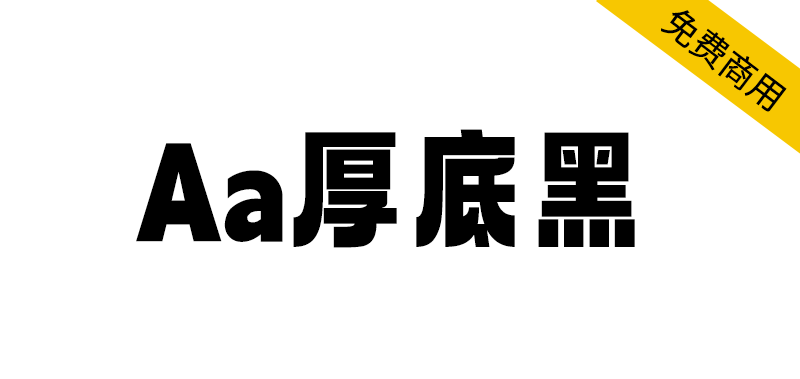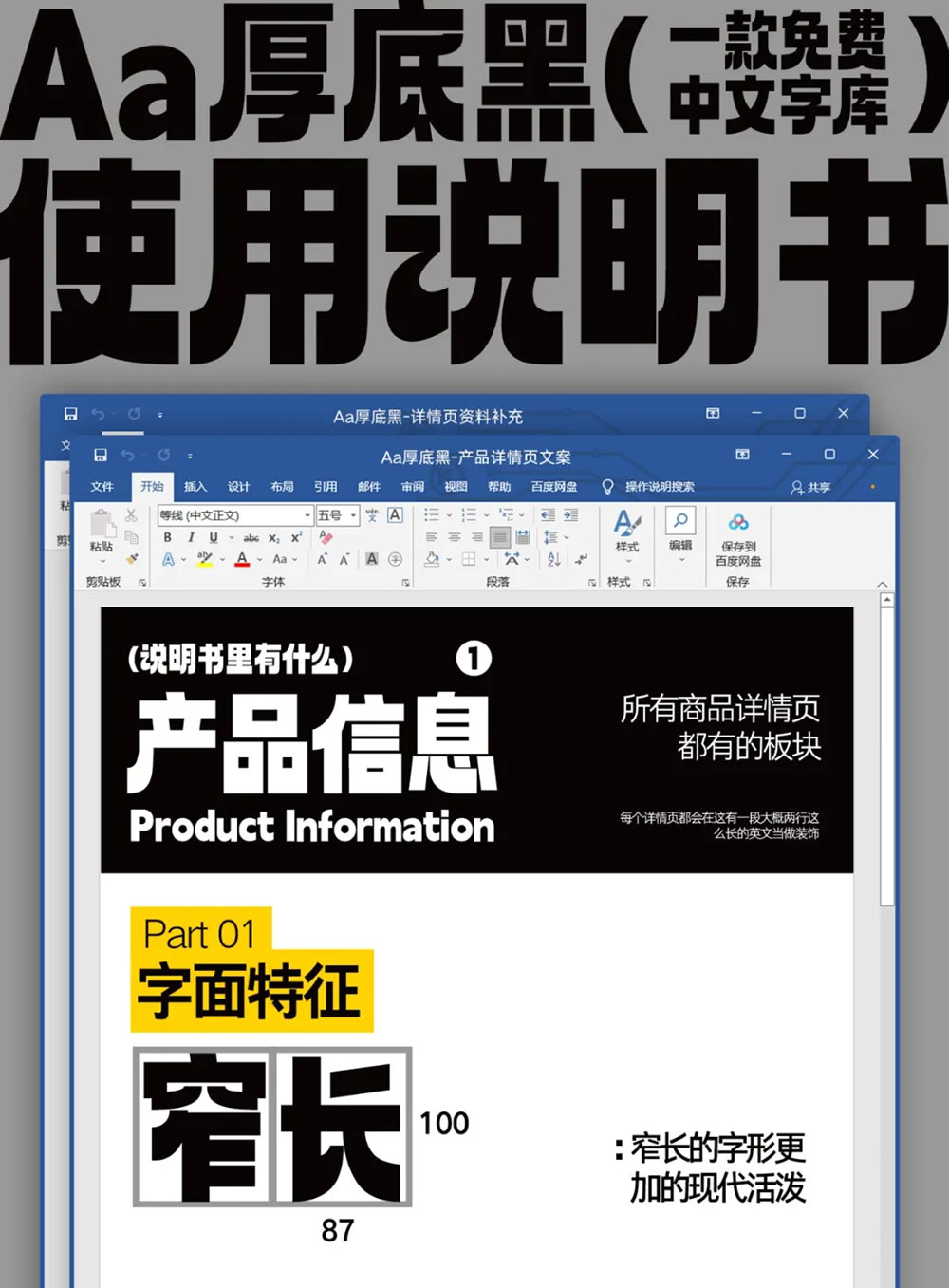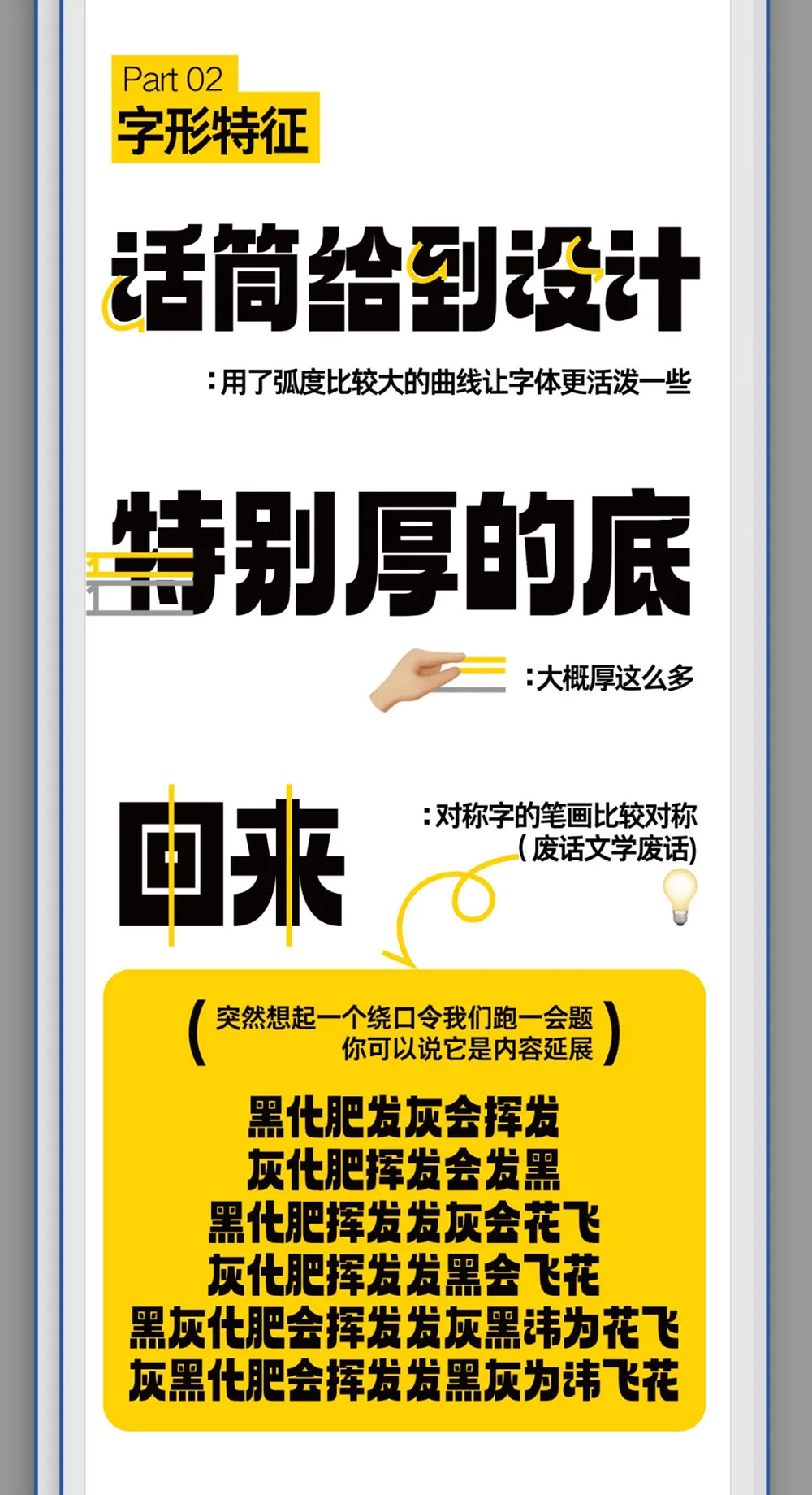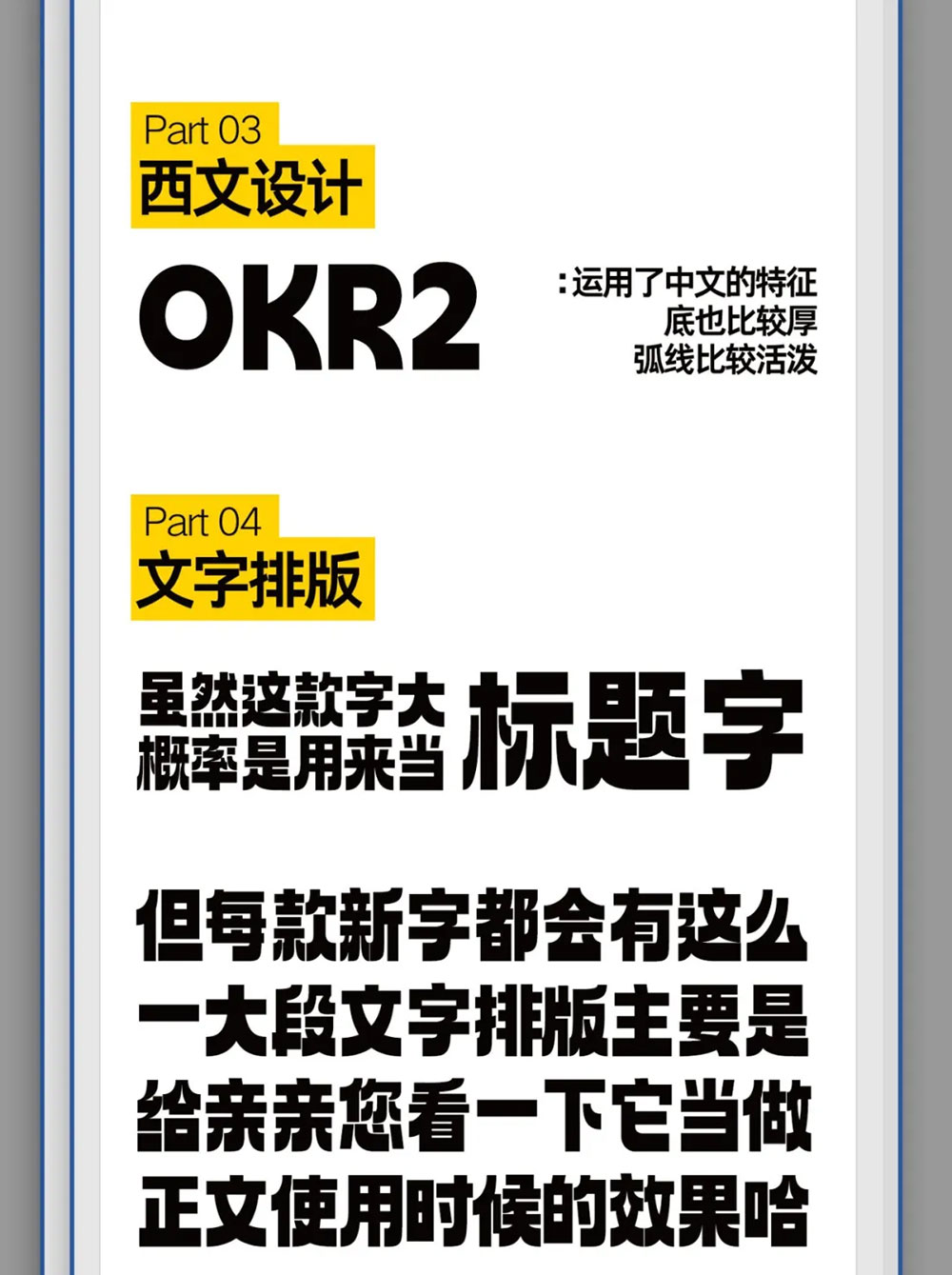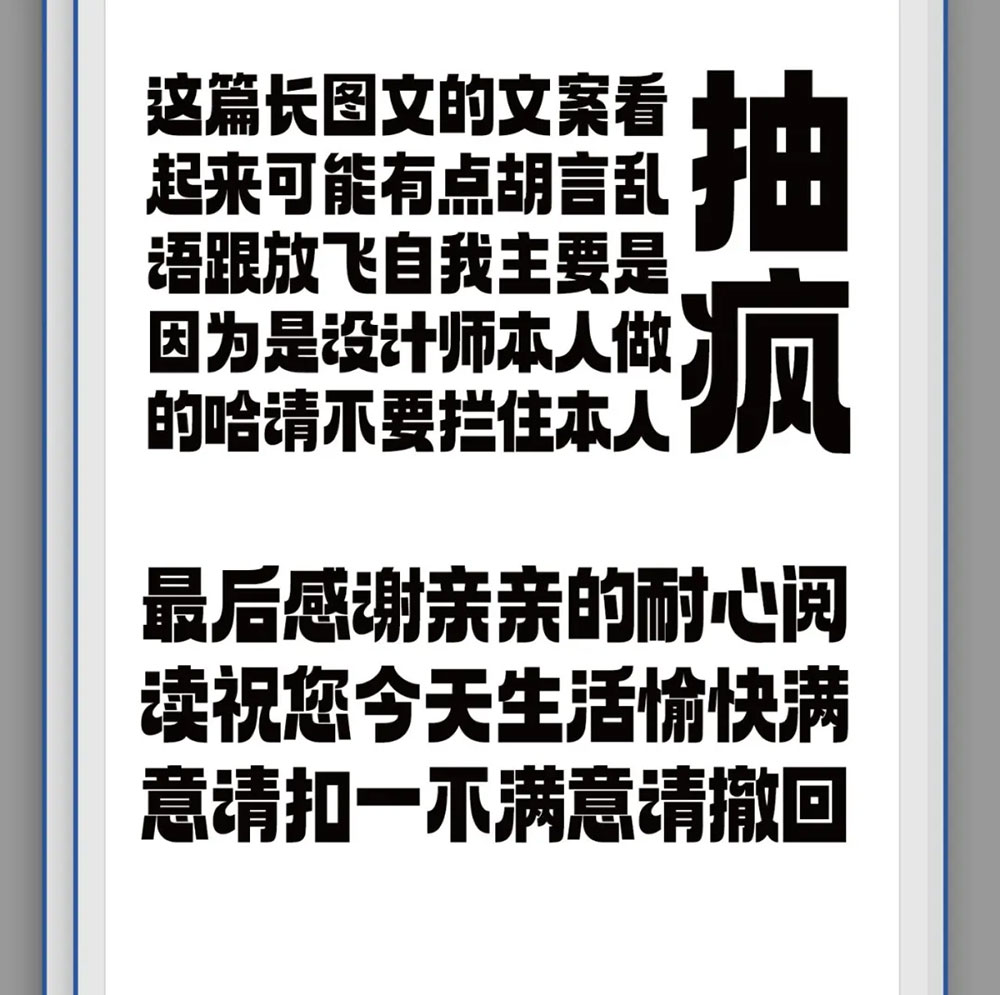
【Aa厚底黑】一款充满现代活泼的免费商用字体
Aa厚底黑是Aa字库推出的一款标题字体,其名称直观体现了字体的核心特征——厚重感与窄长造型的巧妙结合。这款字体在保持粗壮厚重风格的同时,通过修长的字形设计赋予了现代活泼感。
该字体的设计亮点在于:采用大弧度曲线处理,使厚重字形不失灵动;笔画经过精心加粗处理;西文字符完美延续中文字体的设计语言,同样具备厚底特征和流畅弧线。这种独特的设计使其在艺术设计、平面宣传、网页设计等视觉传达领域具有出色的表现力。